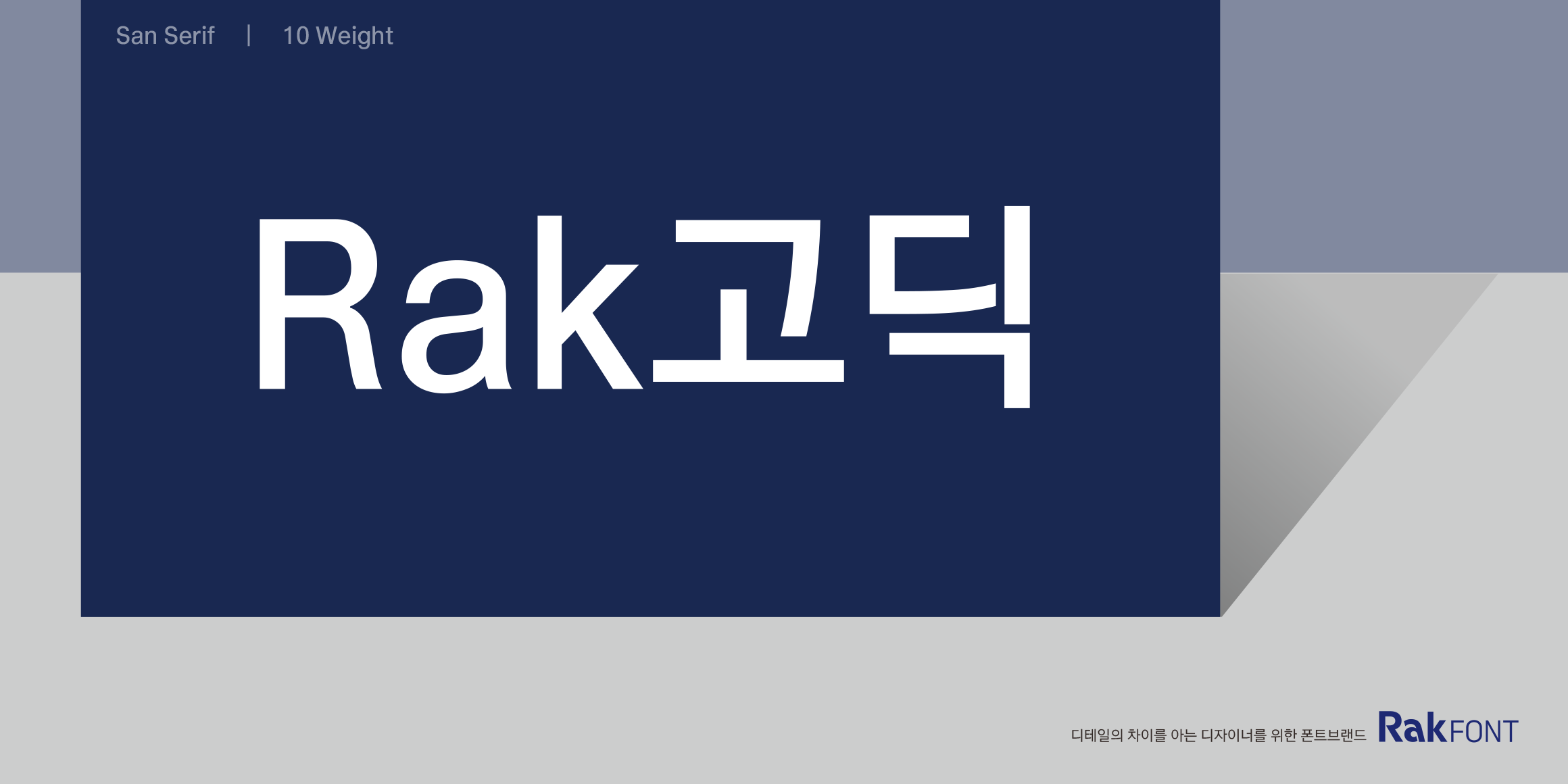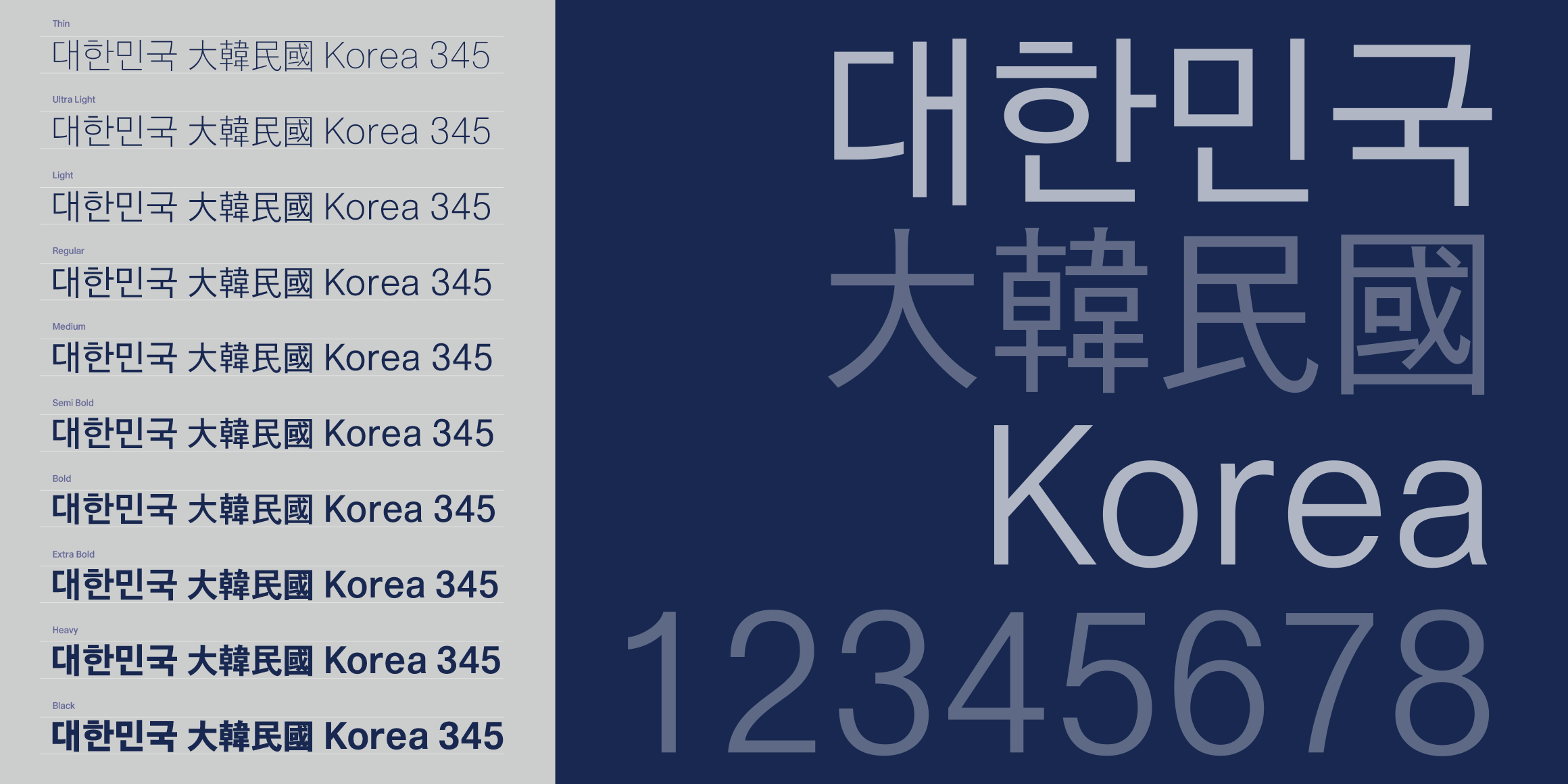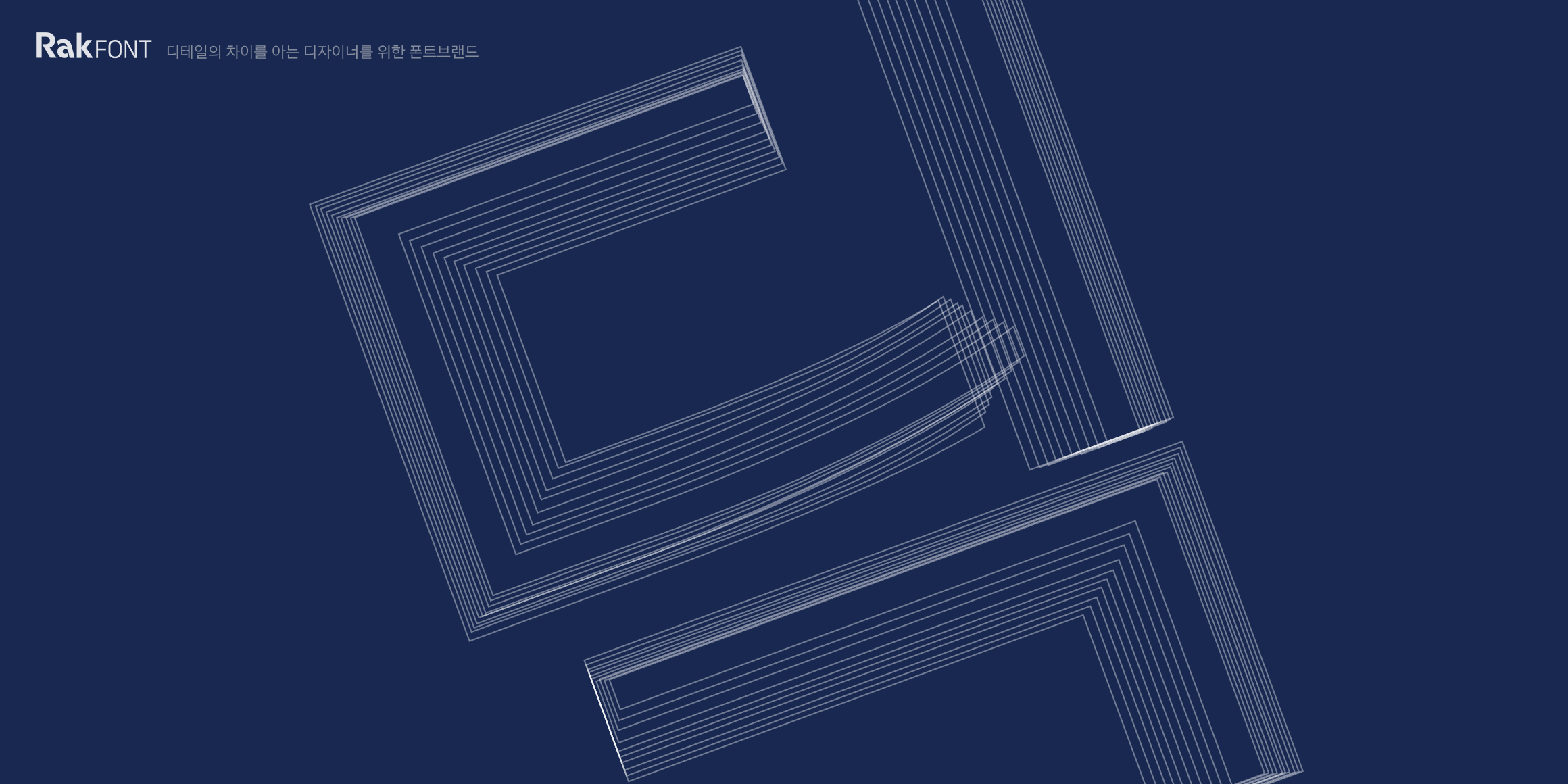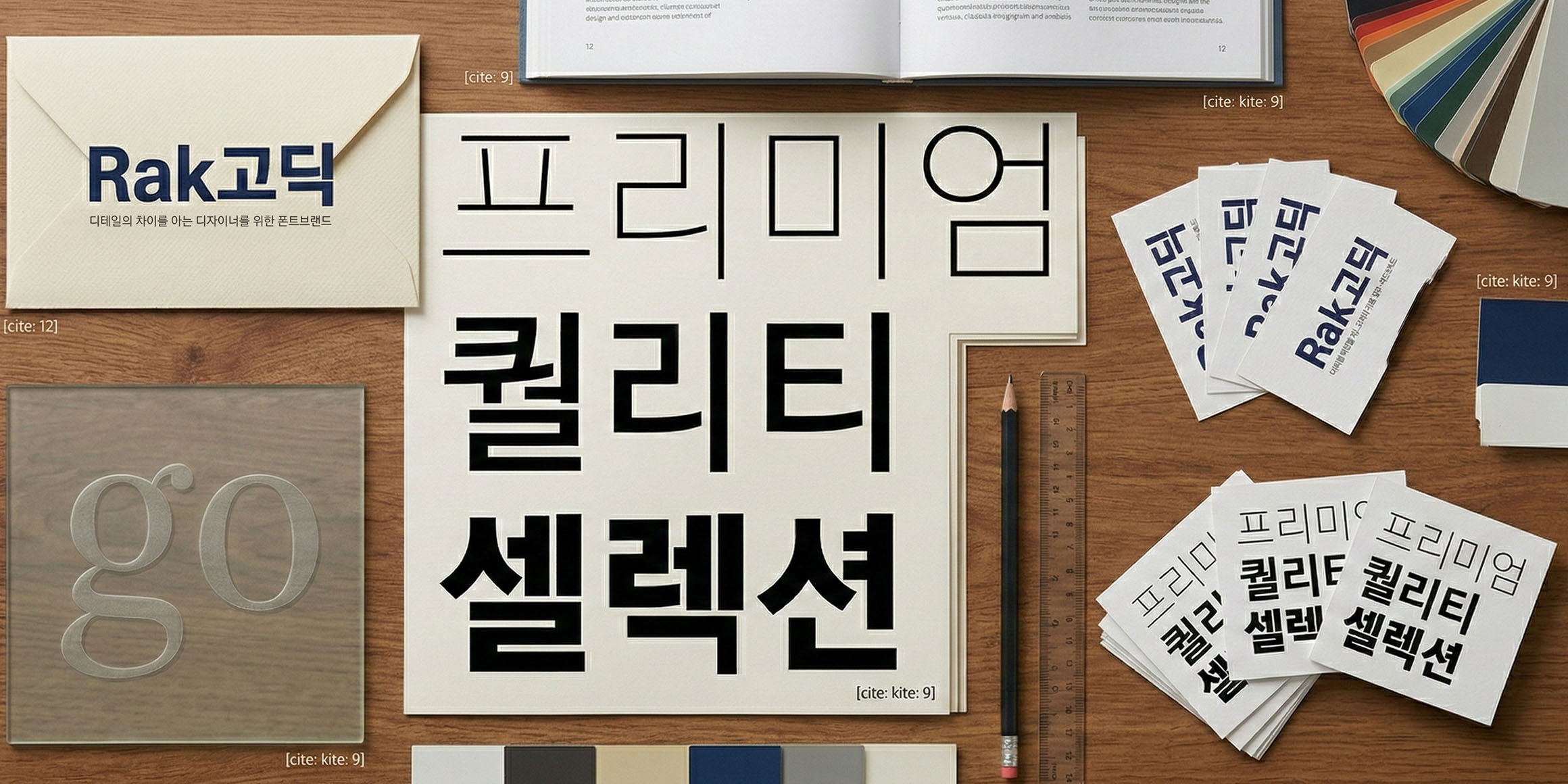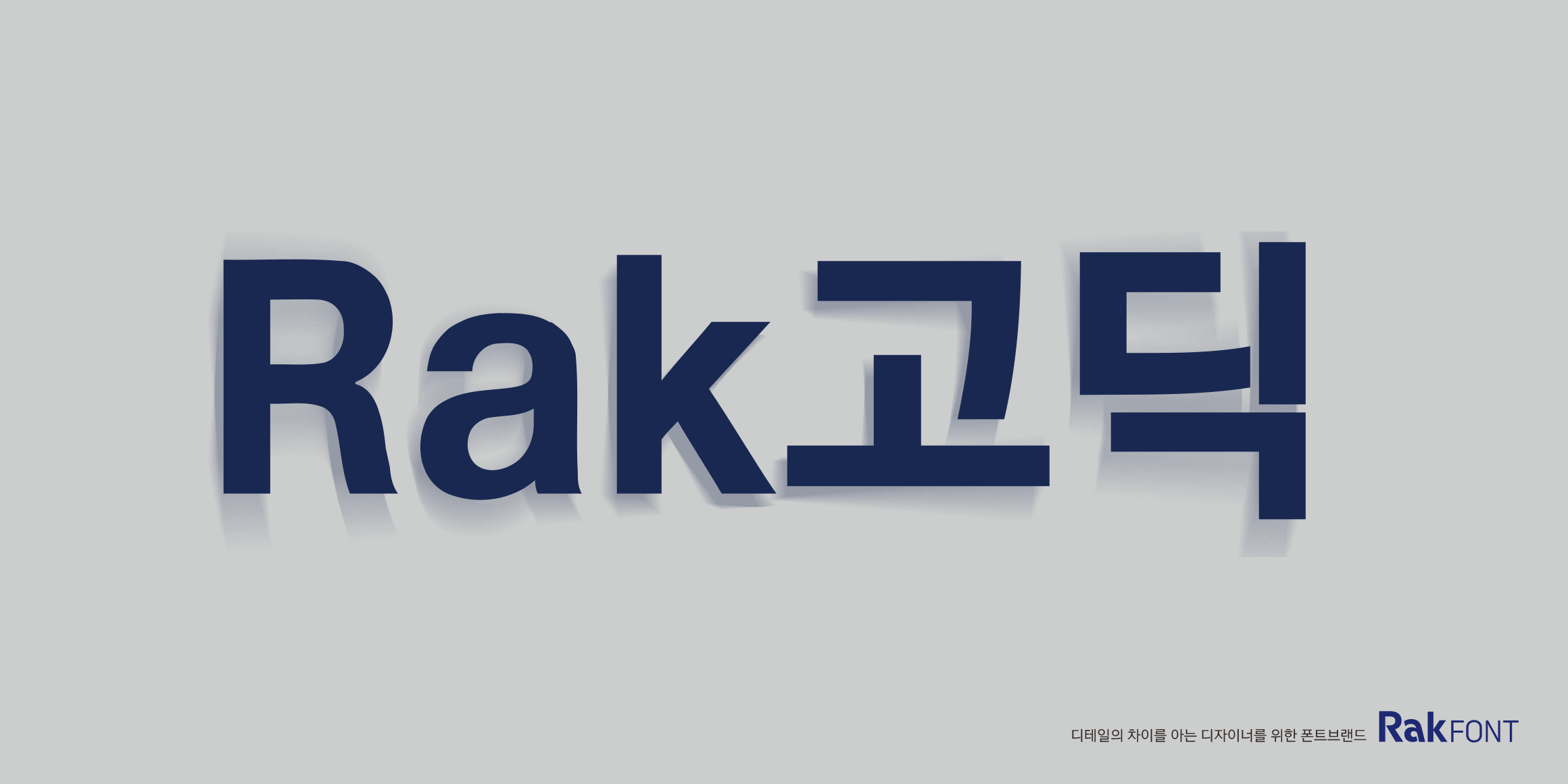
Rak고딕
Rakfont
분류 Gothic,Sans,민부리
종수 10종
25여 년의 폰트 디자인 노하우가 집약된 Rak고딕은 탄탄한 구조와 압도적인 완성도를 자랑합니다. 세밀하게 구성된 다양한 굵기(웨이트)를 지원하여 어떤 환경과 목적에서도 최적의 타이포그래피를 구현할 수 있습니다. 디자이너의 의도를 명확히 전달하며, 모든 콘텐츠의 퀄리티를 한 차원 높여주는 하이엔드 고딕입니다.
• 박용락